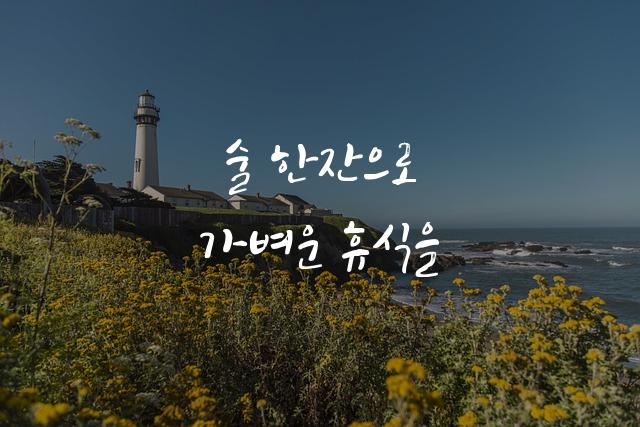
포천오성과한음체는 포천시청에서 제작한 손글씨 고딕 폰트로, 개성있는 독특한 필체가 인상적입니다. 이 폰트는 따뜻하고 친근한 감성을 전달하며, 모던하면서도 전통적인 느낌을 조화롭게 표현합니다.
포천오성과한음체은(는)
기본 고딕, 손글씨, 감성적인 계열의 생김새를 가지고 있으며
출판 디자인, 출판물 제목, 일기/편지 등에서 자주 활용되며, 효과적인 메시지 전달에 적합합니다.
이 폰트는 출판/미디어, 문화/예술, 이벤트/웨딩 분야에 잘 어울리며,
전통적, 편안한, 클래식한 느낌을 담고 있는 것이 특징입니다.